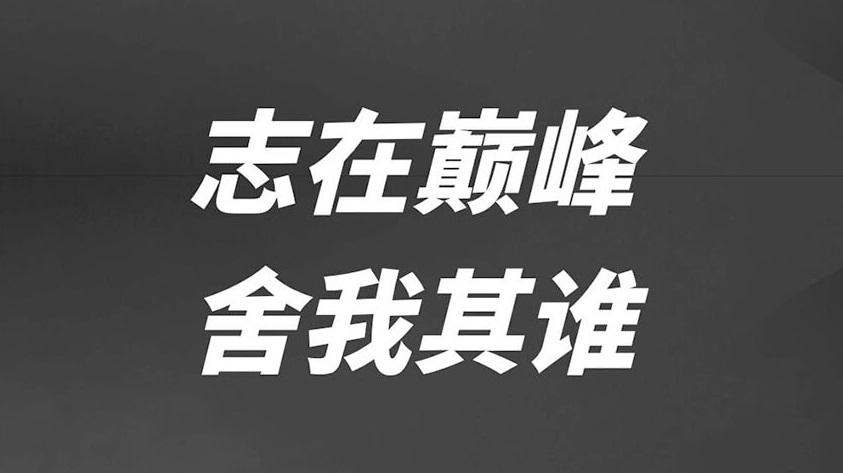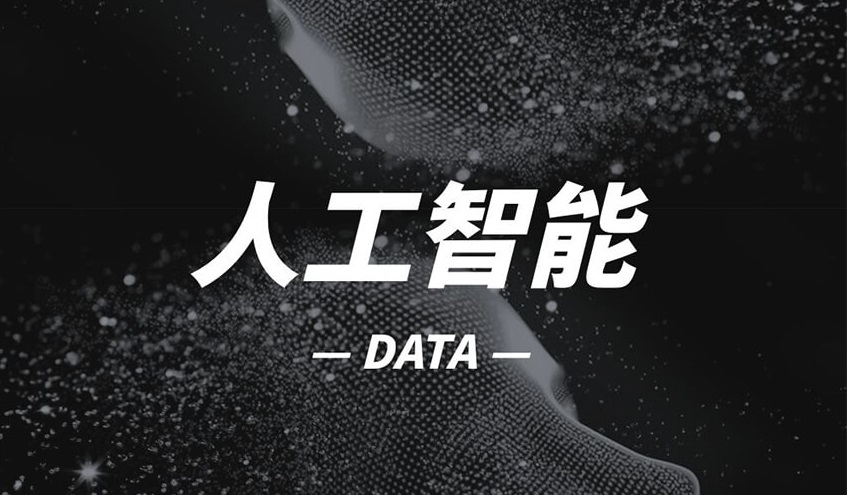
江城斜黑体是一款基于思源黑体改造而成的免费可商用倾斜黑体字体,由设计师刘鹏开发,和江城斜宋体一样,都是为了解决 Keynote 等软件不支持中文倾斜的问题,而且也都是向右上方倾斜 12 度。不同点就是一个是宋体一个是黑体。
笔画粗细均匀,结构端正,无衬线设计简洁有力,很适合科技、商务、时尚、海报、UI 设计等场景。而且江城斜黑体完整覆盖简体中文、繁体中文、日文、韩文、拉丁字母、数字、符号,更是继承了思源黑体从极细(100W)到特粗(900W)的 7 种字重,不管是标题还是正文排版都能满足需求。